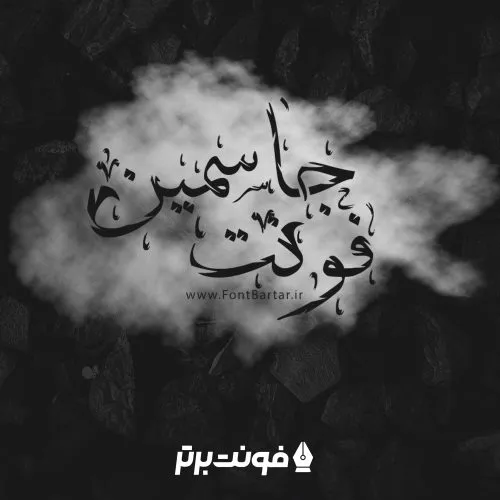
فونت جاسمین
فونت فارسی جاسمین
فونت بسیار زیبا به نام جاسمین در این مطلب سایت فونت برتر برای کاربران عزیز به صورت رایگان گذاشته شده است فونت جاسمین مناسب طراحی پوستر و چاپ و غیره می باشد.
فونت جاسمین مورد استفاده برای:
• طراحان وب سایت و گرافیست های خلاق می توانند از این فونت زیبا فونت در طراحی پروژه های تبلیغاتی و تجاری خود کمک بگیرند.